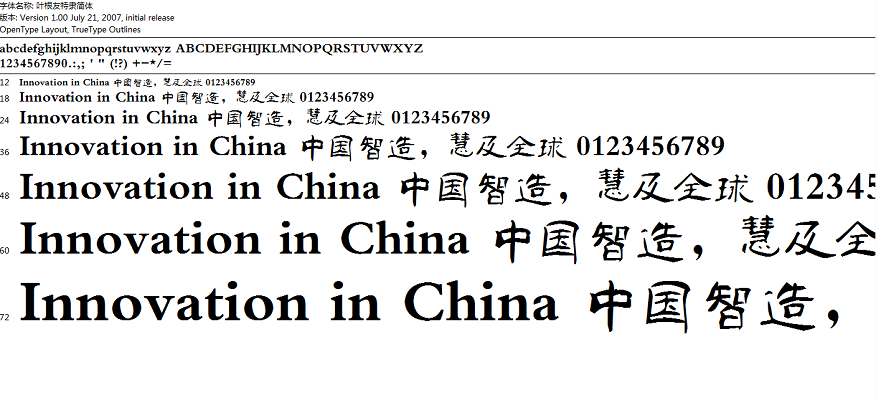
葉根友特隸簡體是一種將楷書與隸書完美融合的特色字體,字體一眼看上去雖隸書元素更大,卻可從中看到楷書之影,可謂是楷中帶隸,隸中求楷,而且字體即有遒勁之威,又不失俊秀之美,是一款非常不錯的書法字體。喜歡這款字體的朋友們快來綠色資源網(wǎng)下載體驗吧!
葉根友隸書字體發(fā)布,該字體是由中國書法奇人,五筆同書世界首創(chuàng)者,連筆空心字吉尼斯世界紀(jì)錄保持者葉根友先生親自書寫的一款字體,字體遒勁俊秀,獨特隸書風(fēng)格,楷中帶隸,隸中求楷。